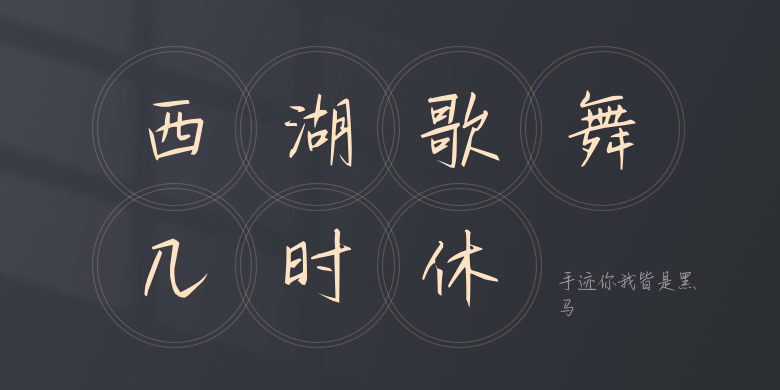
手迹你我皆是黑马
手迹你我皆是黑马,这款字体结构工整、笔画清晰,兼顾美观与易读性,适用于标题、正文、海报、包装、LOGO 等多种场景。字形优雅稳定,风格百搭耐看,适配日常排版与创意设计,让文字呈现更舒适、更具质感。手迹你我皆是黑马一笔一画,皆是细节,以均衡的比例、流畅的线条打造舒适视觉体验,字形端正大气,风格简约现代。无论是商业设计、品牌宣传还是日常排版,都能轻松驾驭,让文字更有格调与力量。手迹你我皆是黑马字体下载。